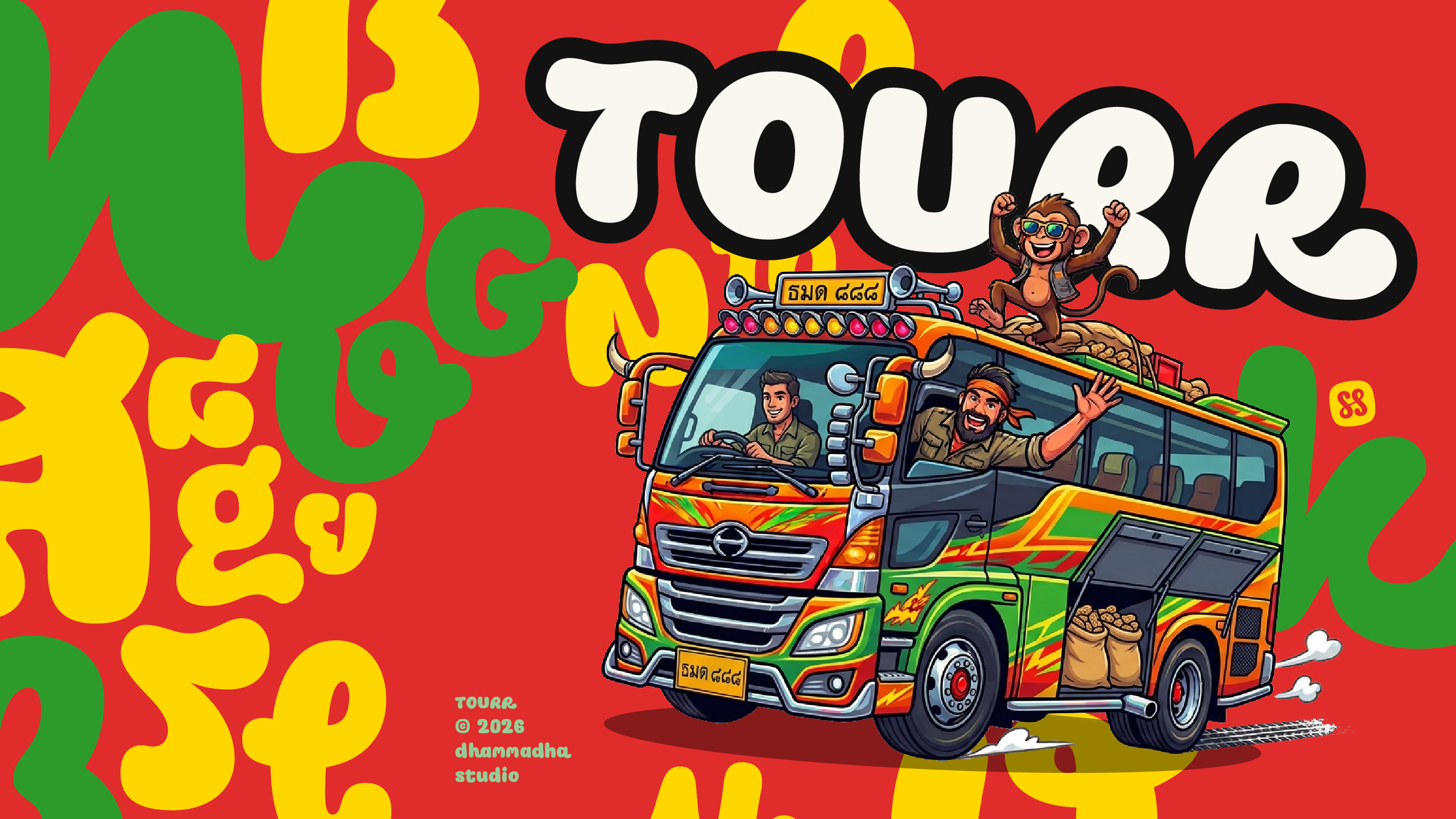
ฟอนต์ “ถั่ว”
ออกแบบโดย ธรรมดาสตูดิโอ
"ถั่ว | TOURR" คือ ฟอนต์ดิสเพลย์สไตล์ลายมือที่พกพาความสนุกสนานและเป็นกันเองมาแบบเต็มพิกัด ฟอนต์นี้เริ่มต้นจากการสเก็ตช์อย่างอิสระบนหน้ากระดาษ ก่อนจะนำมาวาดเส้นสายใหม่บนคอมพิวเตอร์อย่างพิถีพิถัน ทำให้ได้ตัวอักษรที่มีกลิ่นอายความสนุกแบบงานคราฟต์ แต่ยังคงความเนี้ยบและจัดวางได้สวยงามลงตัว ด้วยรูปทรงและน้ำหนักตัวอักษรที่ถูกออกแบบมาให้โดดเด่นสะดุดตา "ถั่ว" จึงเหมาะอย่างยิ่งสำหรับการใช้เป็นพาดหัว (Headline) หรือข้อความที่ต้องการพลังงานบวกและการสื่อสารที่เข้าถึงง่าย ไม่ว่าจะเป็นงานกราฟิกสไตล์โจ๊ะ ๆ คอนเทนต์ไวรัล ป้ายสติ๊กเกอร์ฮา ๆ ท้ายรถกระบะ ไปจนถึงงานออกแบบสายชิล ฟอนต์นี้ก็พร้อมจะเข้าไปช่วยเติมชีวิตชีวาและทำให้ข้อความของคุณตะโกนความบันเทิงออกมาได้อย่างมีสไตล์ นอกจากคาแรคเตอร์ที่ชัดเจนและจัดจ้านแล้ว ฟอนต์ "ถั่ว | TOURR" ยังถูกออกแบบมาให้ตอบโจทย์การใช้งานจริงแบบครบเครื่อง โดยมาพร้อมชุดตัวอักษรภาษาไทย ภาษาอังกฤษ ตัวเลข และสัญลักษณ์พิเศษต่าง ๆ แบบจัดเต็ม ไม่ว่าคุณจะหยิบไปจัดวางพาดหัวบนป้ายโฆษณาขนาดใหญ่ พิมพ์สกรีนข้อความกวน ๆ ลงบนเสื้อยืด หรือสร้างสรรค์อาร์ตเวิร์กสำหรับแคมเปญออนไลน์ ฟอนต์ตัวนี้ก็พร้อมมอบจังหวะสนุก ๆ สไตล์เรกเก้ที่ผสมผสานเข้ากับความเก๋าแบบสิบล้อคลาสสิกได้อย่างลงตัว ช่วยให้ทุกผลงานของคุณดูมีอารมณ์ขัน โดดเด่นจดจำง่าย และยังคงมาตรฐานความประณีตในทุกการจัดวางตามแบบฉบับของธรรมดาสตูดิโอเช่นเคย